80 kiểu chữ (typeface) dành cho pro Designer (hết)
Nối tiếp hai phần trước chúng ta tiếp tục liệt kê những font chữ dành cho nhà thiết kế chuyên nghiệp. Qua toàn bộ cả ba phần bạn có thể thấy những phông chữ được những thiết kế chuyên nghiệp chọn thường đề cao sự đơn giản, khoẻ khoắn, mạn mẽ. Mong rằng bạn có thêm tư liệu cho các thiết kế typography của mình.
61. Depot
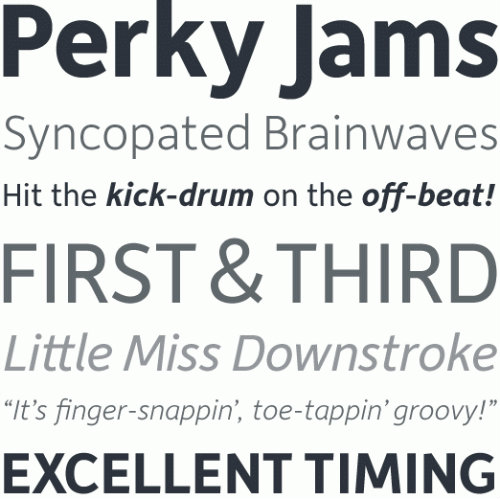
62. Priva Pro
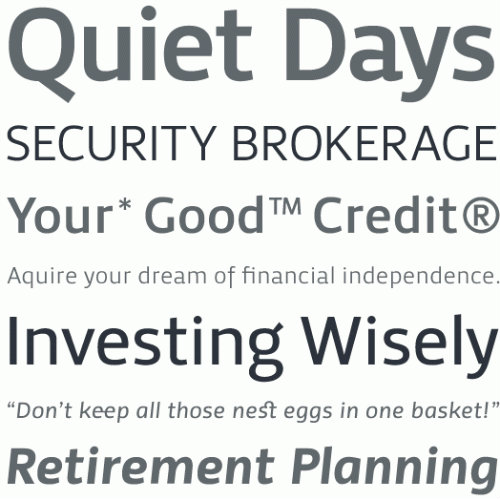
63. Whitman
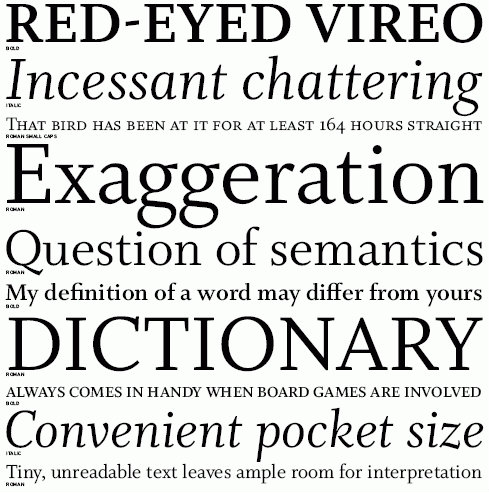
64. Productus
65. Tempelhof
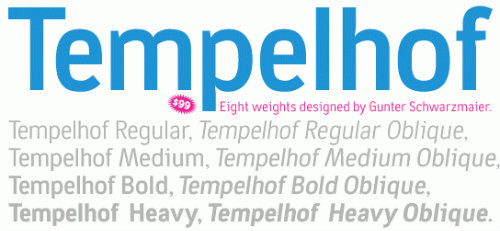
66. Amira
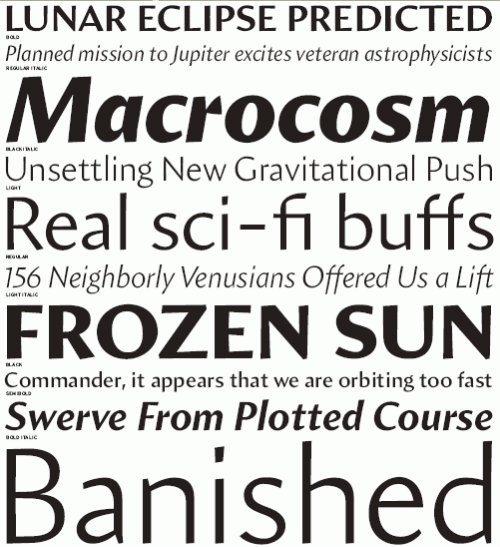
67. Krart
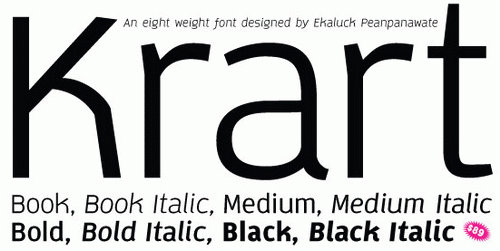
68. Tang
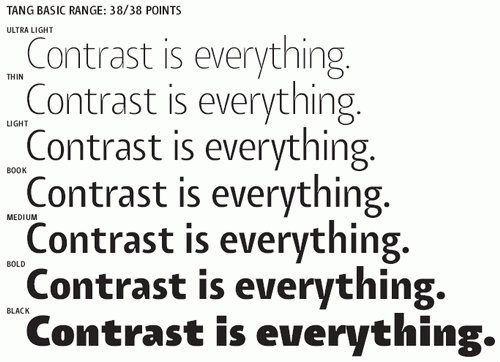
69. Dederon Sans
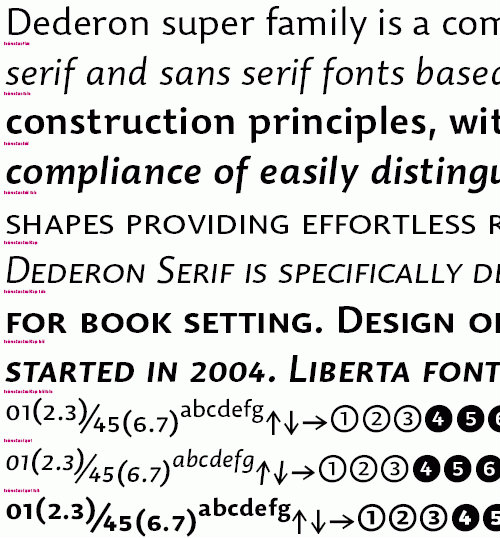
70. Samuels Family
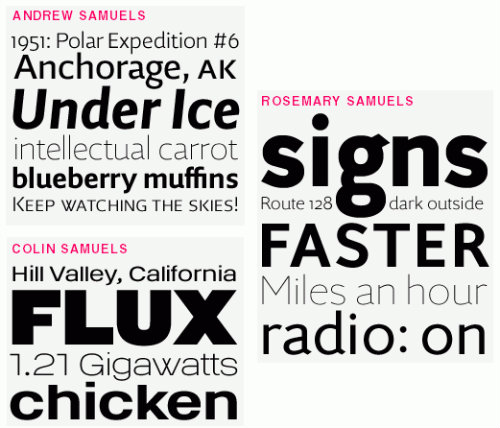
71. Untitled
72. Greta Text
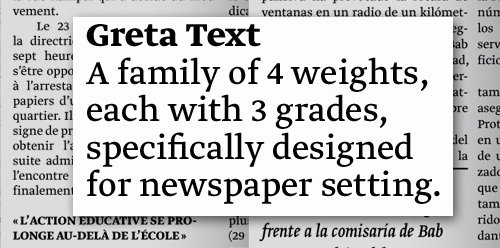
73. FF Sanuk
74. Houschka
75. Scene
76. Amplitude
77. Insider
78. Preface
79. Flex
80. Halvorsen
81. Xtra Sans
Những font có được giới thiệu thêm sau bài viết này.
82. Obliqua (in development)
83. Muestra Urbana (in development)
83. Wingardium
84. Tauran Regular
85. Mello Sans